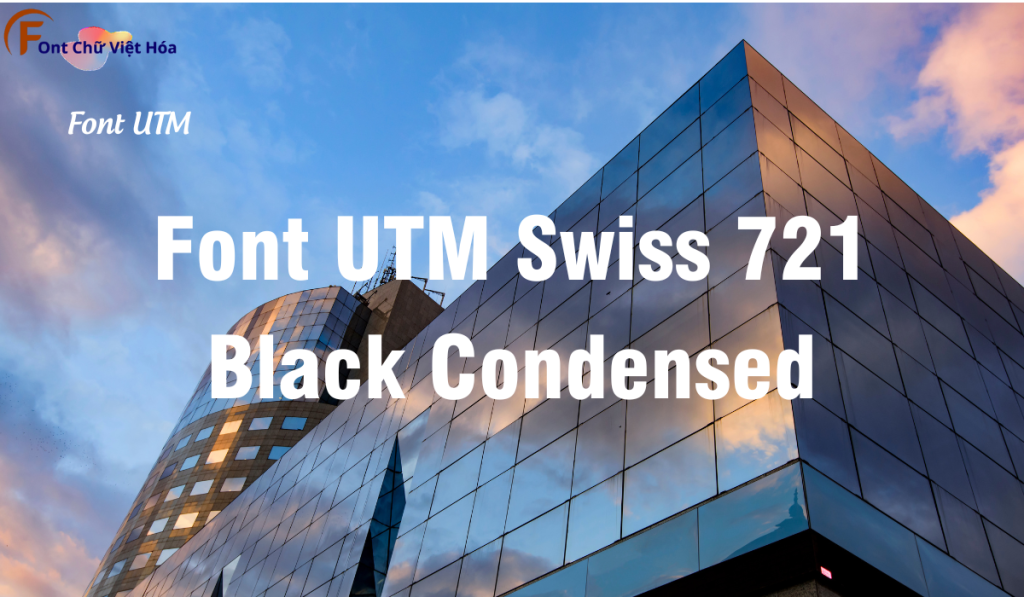
Font UTM Swiss 721 Black Condensed Việt Hóa
Tác giả: UTM Swiss 721 Black Condensed
Bộ Font: UTM
Độ dày: Black
Font UTM Swiss 721 Black Condensed Việt Hóa là một font chữ không chân mạnh mẽ, thuộc bộ font UTM. Được thiết kế với mục tiêu mang lại sự hiện đại và năng động, font này lý tưởng cho các dự án thiết kế như logo, poster, và bao bì sản phẩm. Với các nét chữ rõ ràng và độ dày đều đặn, Font UTM Swiss 721 Black Condensed Việt Hóa không chỉ dễ đọc mà còn tạo cảm giác mạnh mẽ và hiện đại. Việc Việt hóa font giúp người dùng dễ dàng tích hợp vào các thiết kế tiếng Việt, mang lại sự tiện lợi và nâng cao tính thẩm mỹ.